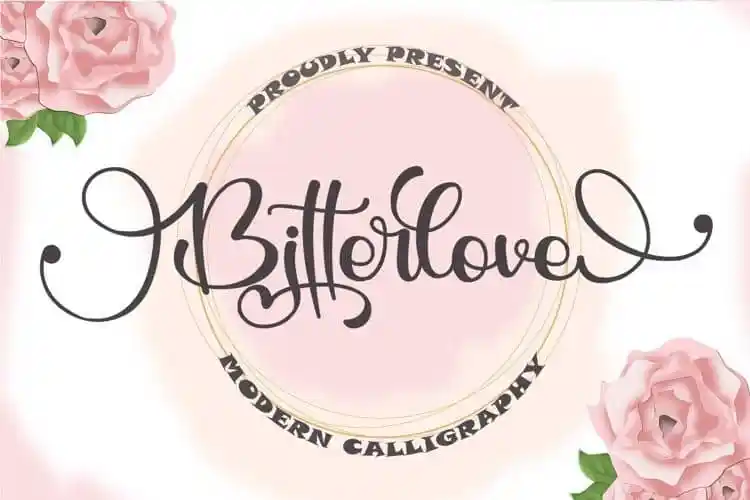
Bitterlove Calligraphy Font
A Bitterlove Calligraphy Font é uma elegante farta de letras romântica e moderna criada pela Letterafa Studio. Perfeita para diversos projetos de design, essa fonte oferece linhas fluidas que adicionam um look único e suave a seus designs, com muitos caracteres encantadores. A Bitterlove é ideal para logomarcas, cartões de felicitações, desenho de embalagens, identidade de marca, arte em DIY, títulos de livros, convites de casamento ou qualquer projeto envolto em uma atmosfera de romantismo moderno. Experimente a Bitterlove para revolucionar sua abordagem ao design e trazer um toque romântico moderno a todos os seus projetos.